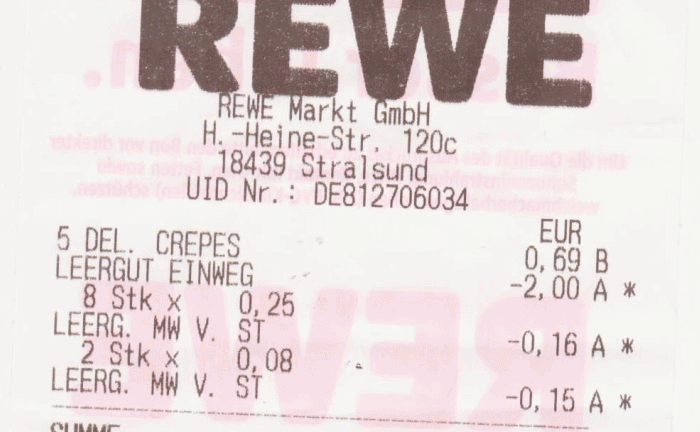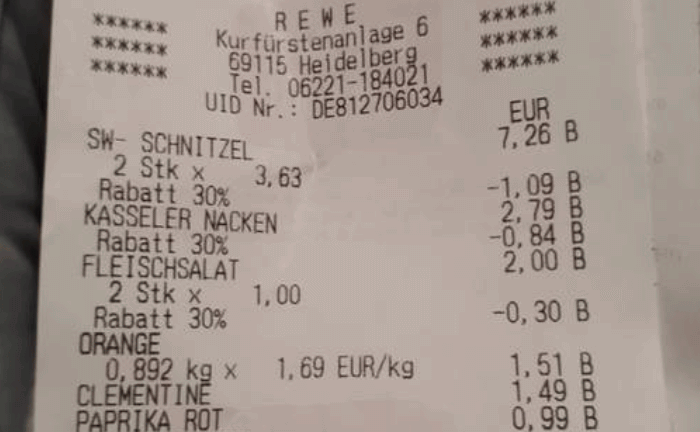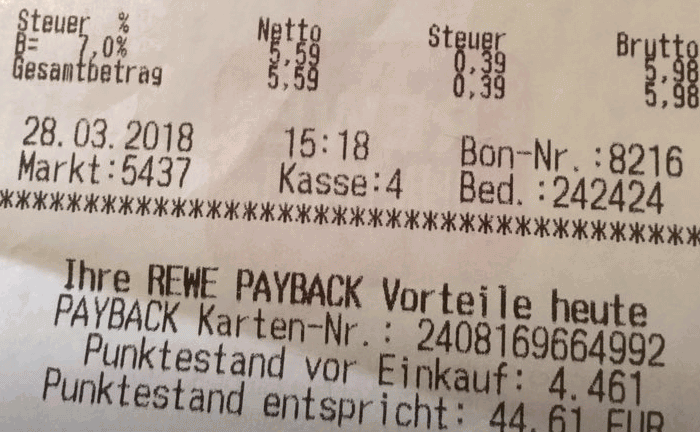
Eine ungewöhnliche Schriftart, die häufig auf Kassenbons in Rewe-Supermärkten zu finden ist
Achten Sie auf die Schreibweise der drei Zahlen 569 in dieser Schriftart
Alle Zeichen der Schriftart⤴
gedrucktes Sample von der Schriftart⤴